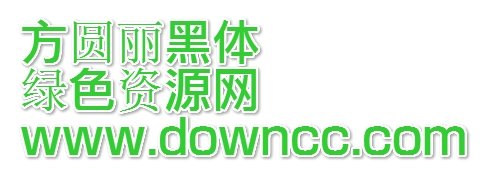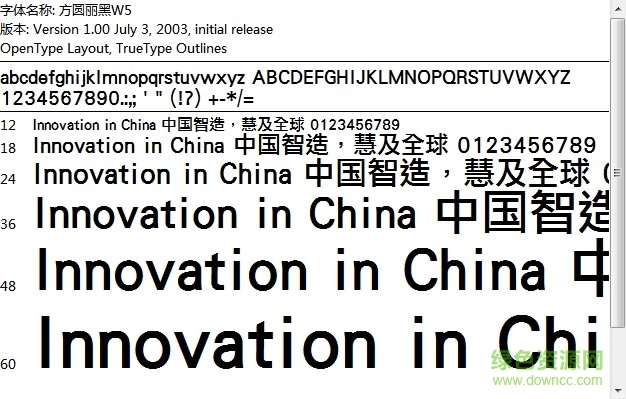
方圓麗黑體是一款支持繁體輸入的黑體字體,整體十分清爽大氣,有著厚重的字形和沉穩(wěn)的結(jié)構(gòu),讓文字更加明亮整潔,喜歡的朋友不妨來(lái)綠色資源網(wǎng)下載體驗(yàn)哦!
方圓新麗黑,簡(jiǎn)潔大方,字形端正,是一款設(shè)計(jì)精美的中文藝術(shù)字體,字庫(kù)完整,適合數(shù)字媒體、包裝設(shè)計(jì)、廣告設(shè)計(jì)、網(wǎng)頁(yè)設(shè)計(jì)等設(shè)計(jì)場(chǎng)合!